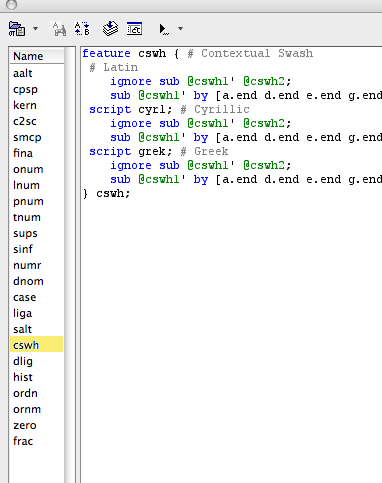
FireFox 4.0.1: OpenType - Alternative Buchstaben
auf meiner Webseite (die noch in Arbeit ist) verwende ich die Schriftart "Warnock Pro". Diese Schriftart hat für einige Buchstaben gesonderte Glyphen als Schmuckversionen für das Wortende, die allerdings für einen Fließtext nicht geeignet, sondern eher für Überschriften gedacht sind.
Ich vermute, dass die Glyphenersetzung in der Schrifart selbst hinterlegt ist. Diese Feature verwendet wohl FF ab der Version 4.0.1; kann ich das irgendwie (durch eine Konfigurationseinstellung) unterbinden oder muss ich die Schriftart aktualisieren?
Zu dem Problem:
Mit der CSS-Anweisung
text-rendering: optimizeSpeed;[/CODE]
kannst du die Ligaturen ausschalten.
Zu dem Problem:
text-rendering: optimizeSpeed;[/CODE]
kannst du die Ligaturen ausschalten.
Gute Idee; funktioniert aber leider nicht. Habe das StyleSheet entsprechend angepasst, aber keine Änderung erwirken können. Diese Buchstabenformen sind ja meines Wissens auch keine Ligaturen; oder gelten auch Kombination mit Leerzeichen und/oder Satzendezeichen auch als Ligaturen? Ich kenne mich "technisch" mit den speziellen Möglichkeiten von TTF/OTF nicht besonders gut aus; weiss aber um die mächtigen Möglichkeiten bspw. die Unzahl an Ligaturen im Sanskrit, die in Sanskrit 2003 hinterlegt sind.
Nachtrag:
Dein Vorschlag war ein guter Ausgangpunkt. In einem späteren Beitrag in diesem Formum werden die OpenType-Fähigkeiten von FF4 zur Kenntnis gestellt. Mittels
[CODE]-moz-font-feature-settings: "liga=0";[/CODE]
kann ich tatsächlich die "üblichen" Ligaturen ausschalten. Die alternative Buchstabenform allerdings nicht. Auch hilft die Anweisung für "swash character" leider nicht weiter.
Hier ein Bild der Features der Warnock Pro. Eines davon isses. Ich tippe, ohne es probiert zu haben, auf CSWH als Ursache. Setzt das mal auf Null.
Ok, mit
-moz-font-feature-settings: "cswh=0";[/CODE]
funktioniert es. Vielen Dank!
P.S.: Ich vermute mal, dass du dieses Feature via FontLab Studio ermittelt hast. Wenn ich mich diese Thematik einarbeiten wollte, kennst Du dafür Quellen? Keine Sorge: genügend Programmier- und Grundkenntnisse der Typographie sind durchaus vorhanden.